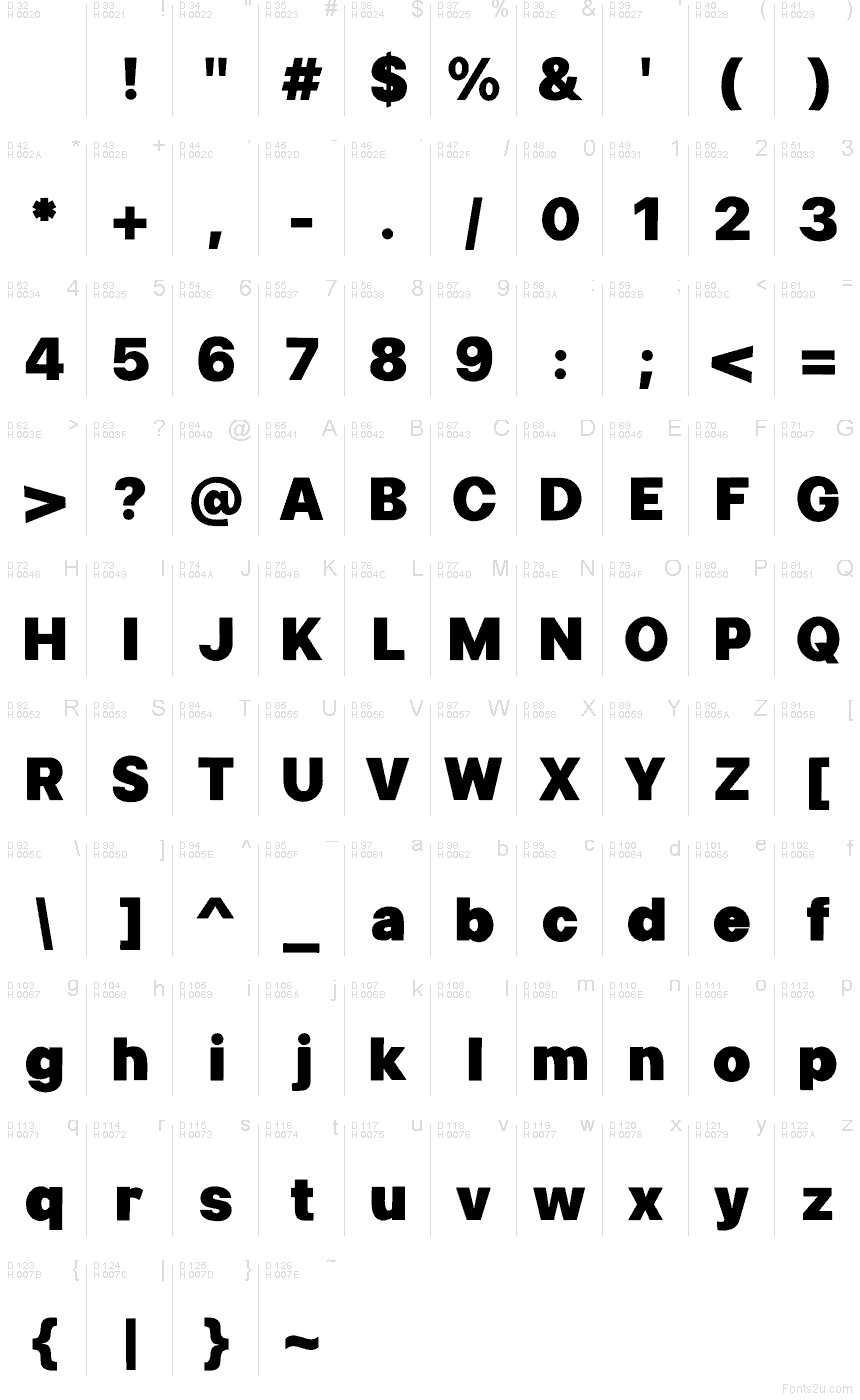
Durobang від Hello Good Studio - це безкоштовний беззарубковий шрифт із щільним округлим силуетом, завдяки якому кожна літера виглядає як цілісний графічний елемент. Широкі криві, глибокі вирізи та компактний ритм надають дизайну м’якої, «вагомої» присутності, на противагу гострому характеру типових геометричних шрифтів.
Така графічна виразність ідеально підходить для логотипів, заголовків на плакатах, обкладинок альбомів, пакування та банерів у соцмережах, де літери мають бути не лише текстом, а й яскравою формою. Шрифт також чудово пасує до дитячих брендів та етикеток харчових продуктів: його повні форми виглядають дружньо та ґрунтовно, а не суворо чи технічно.
Durobang